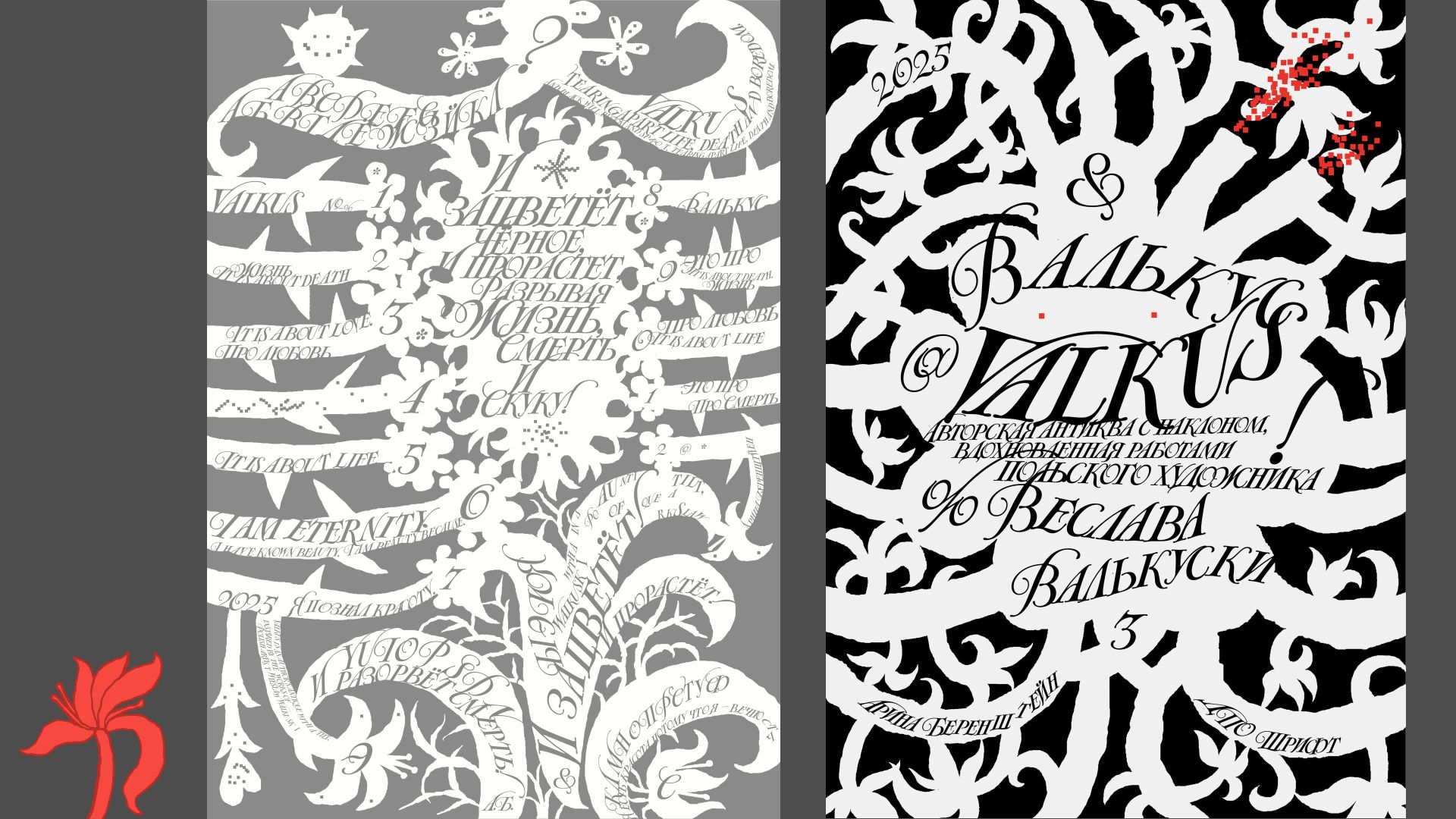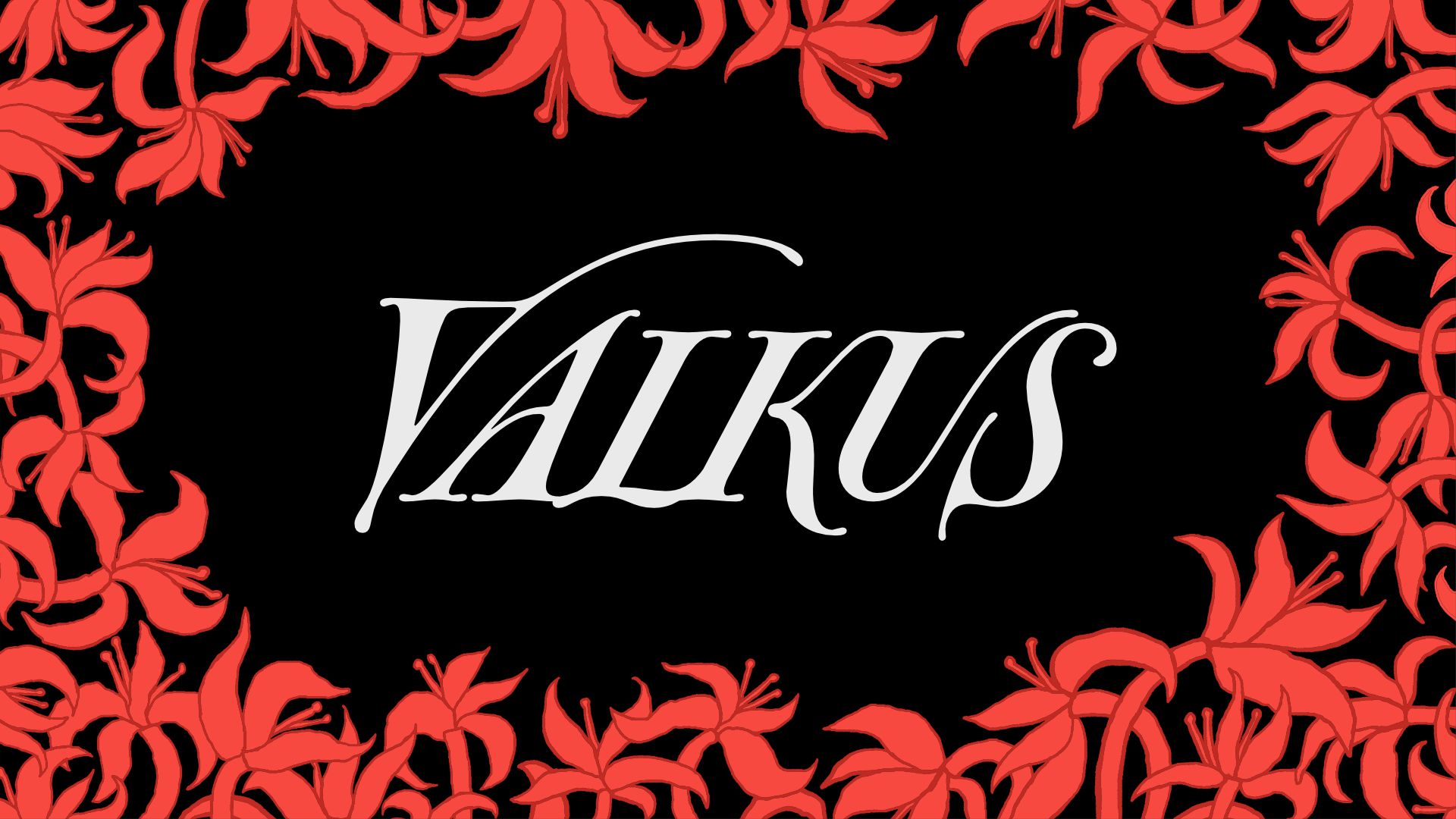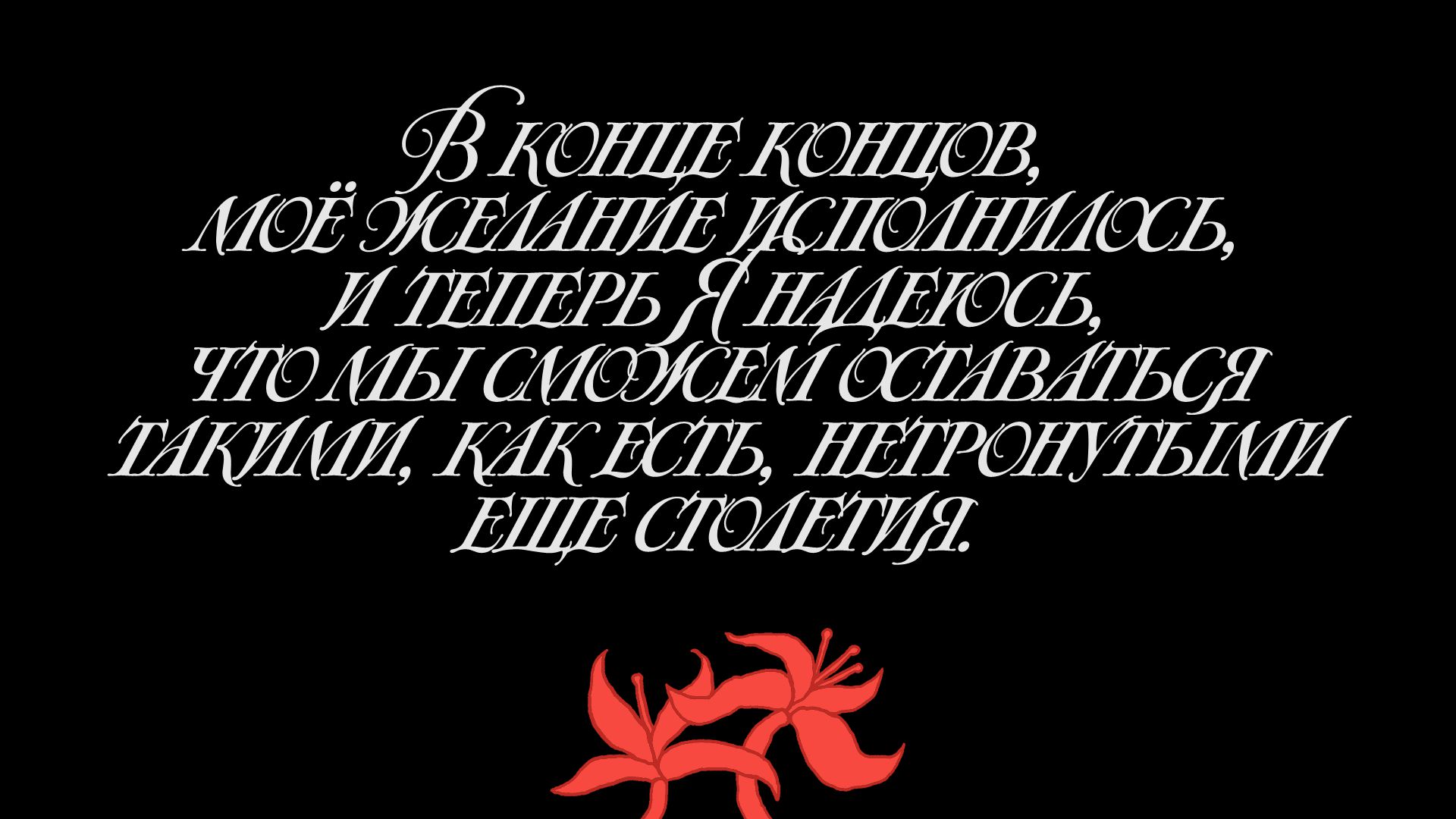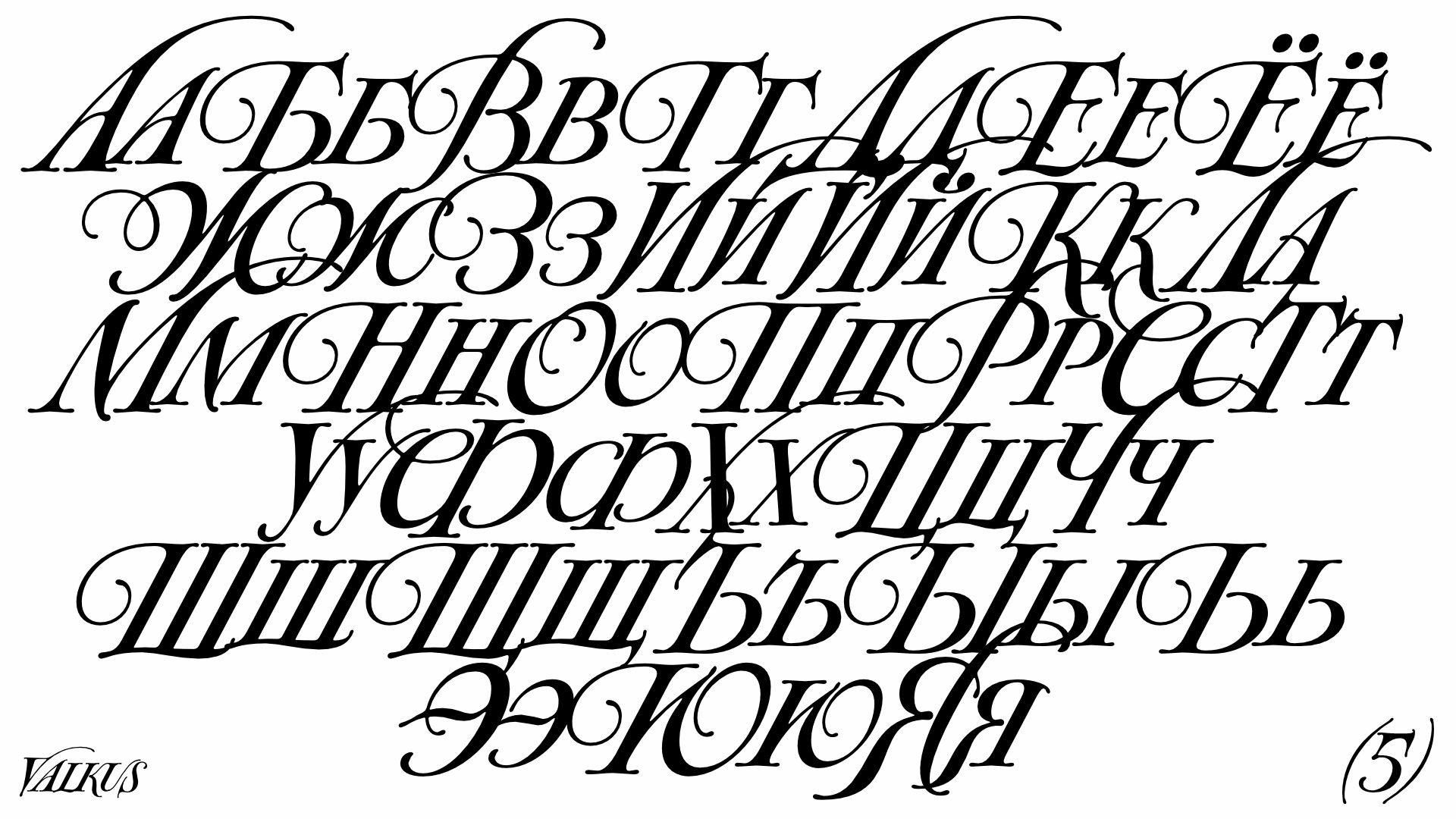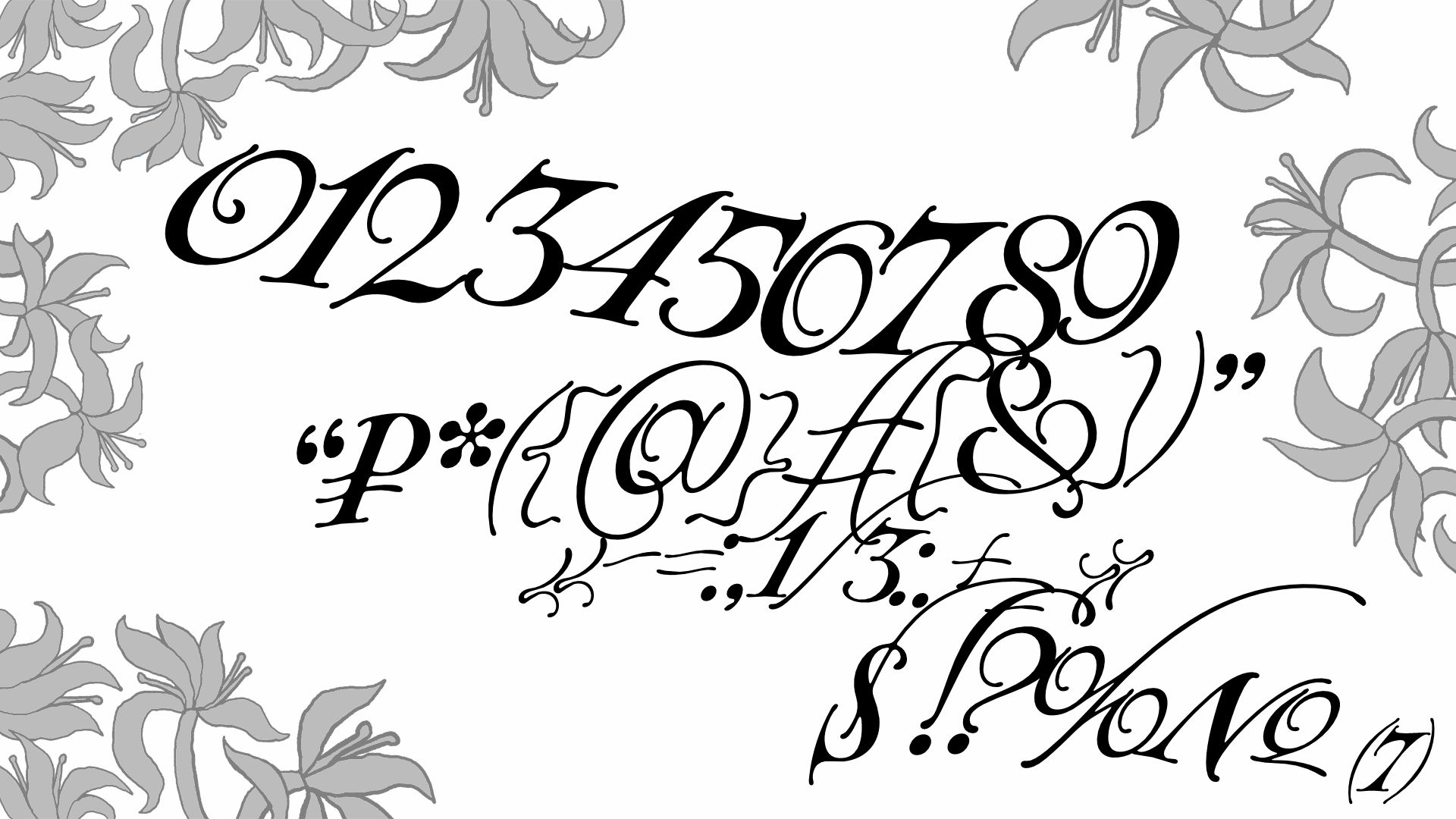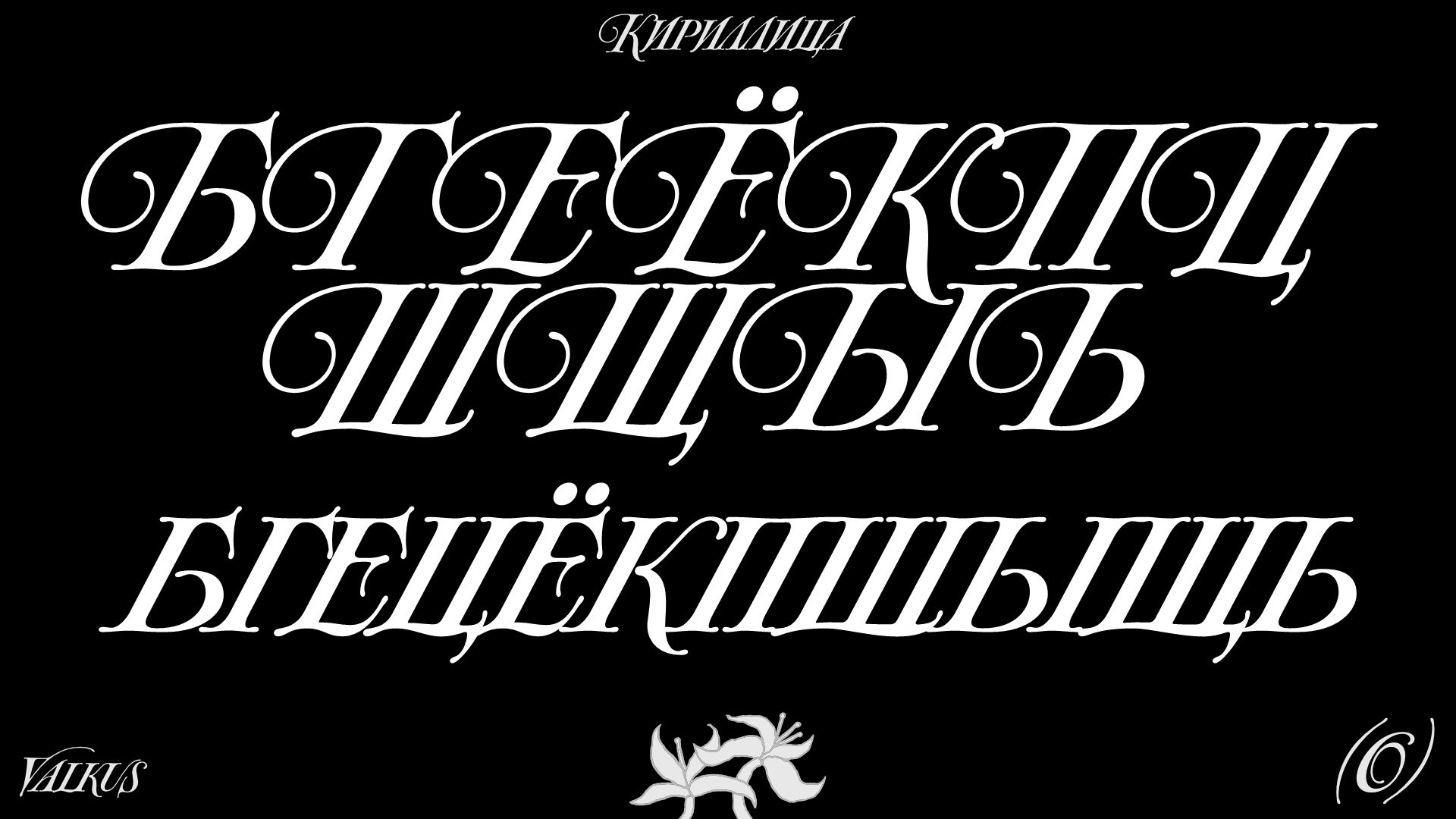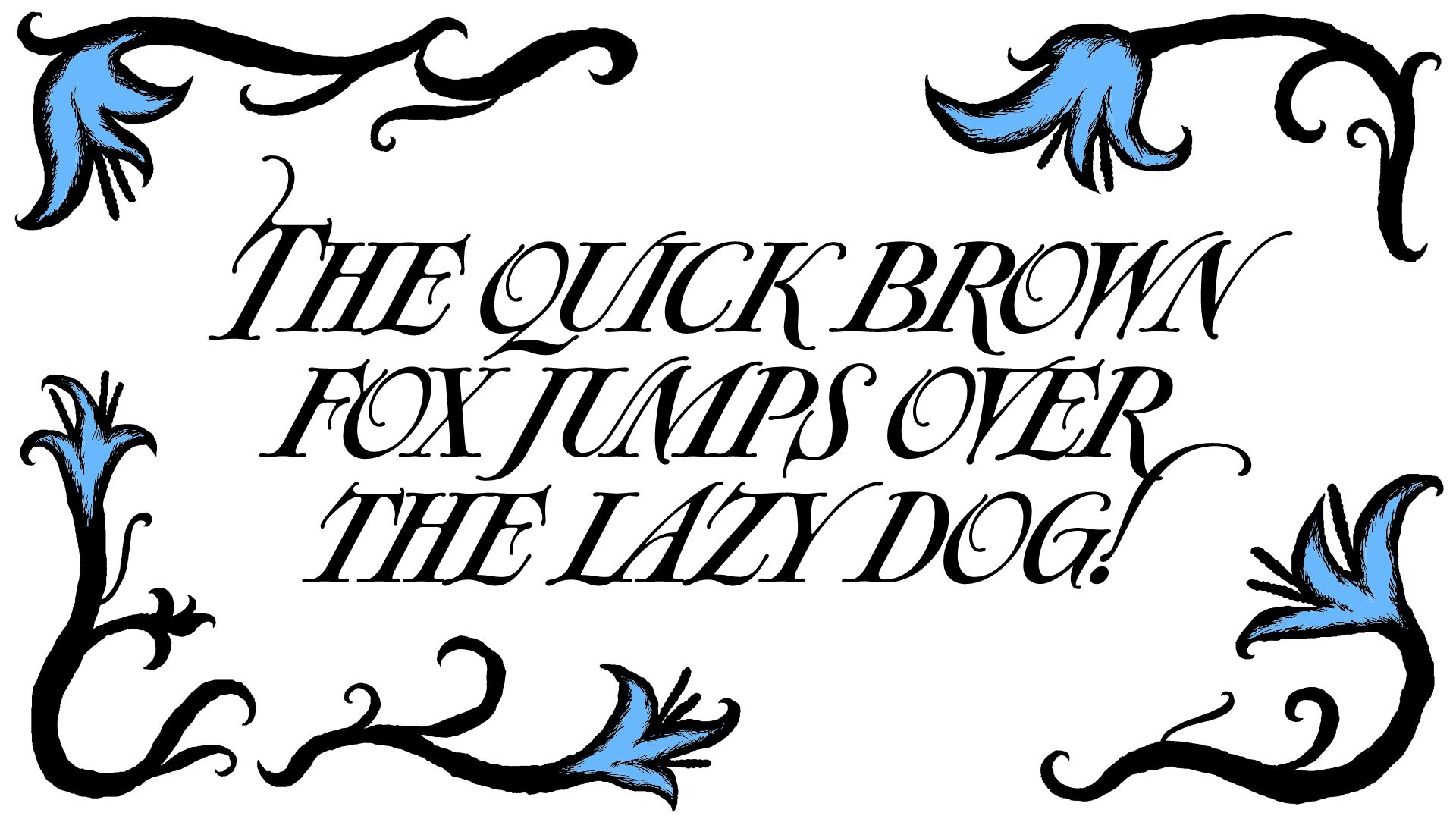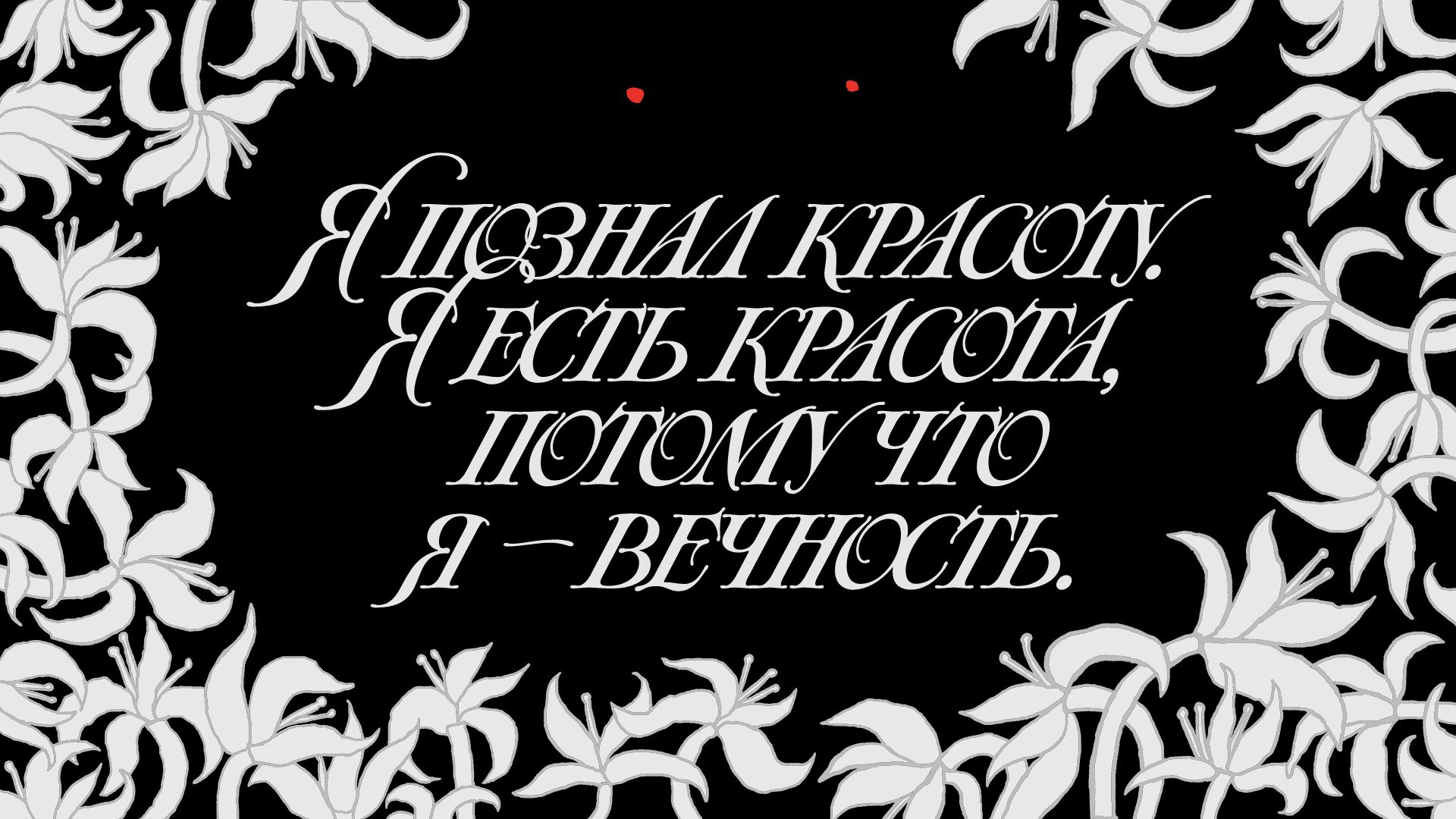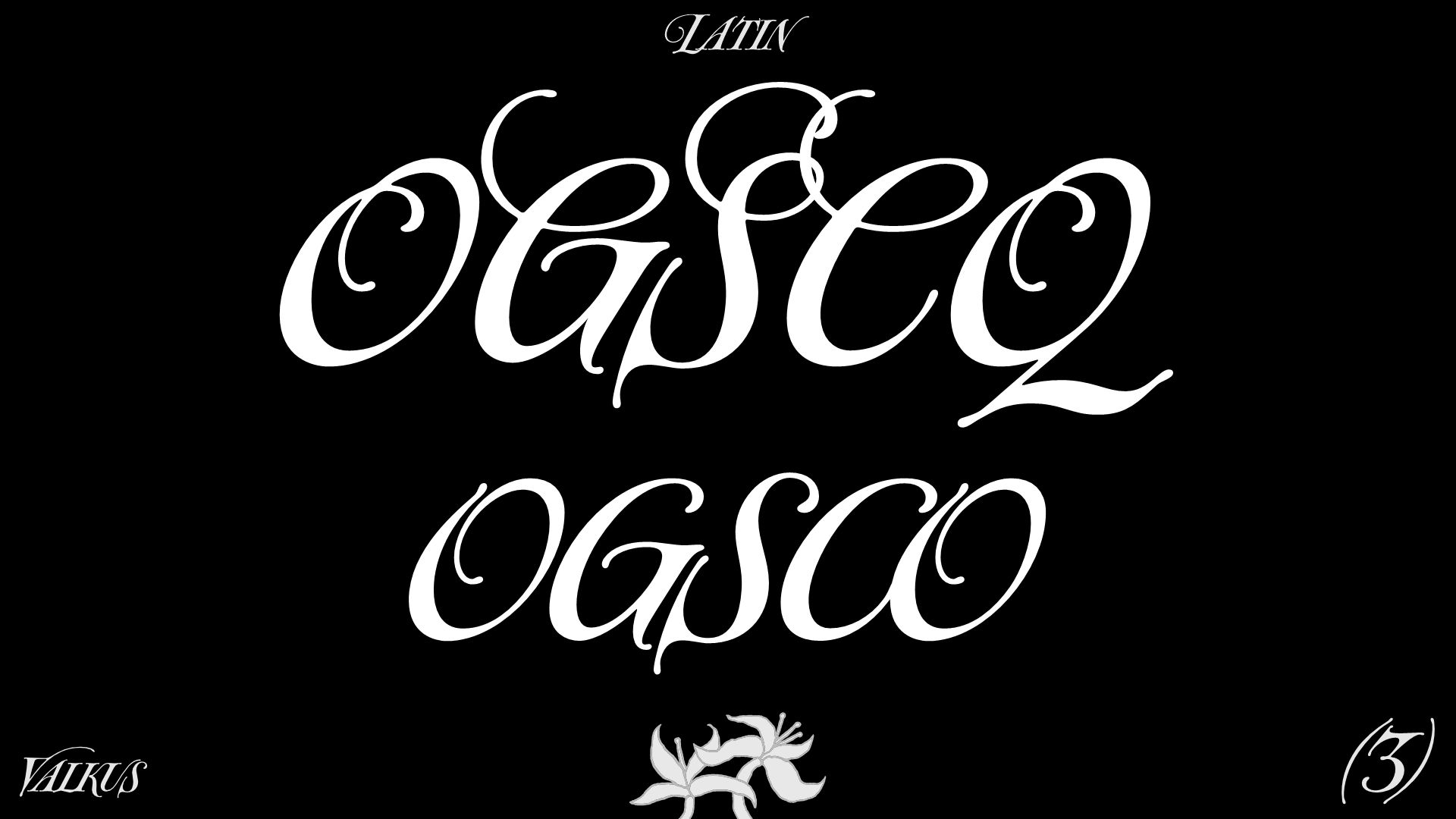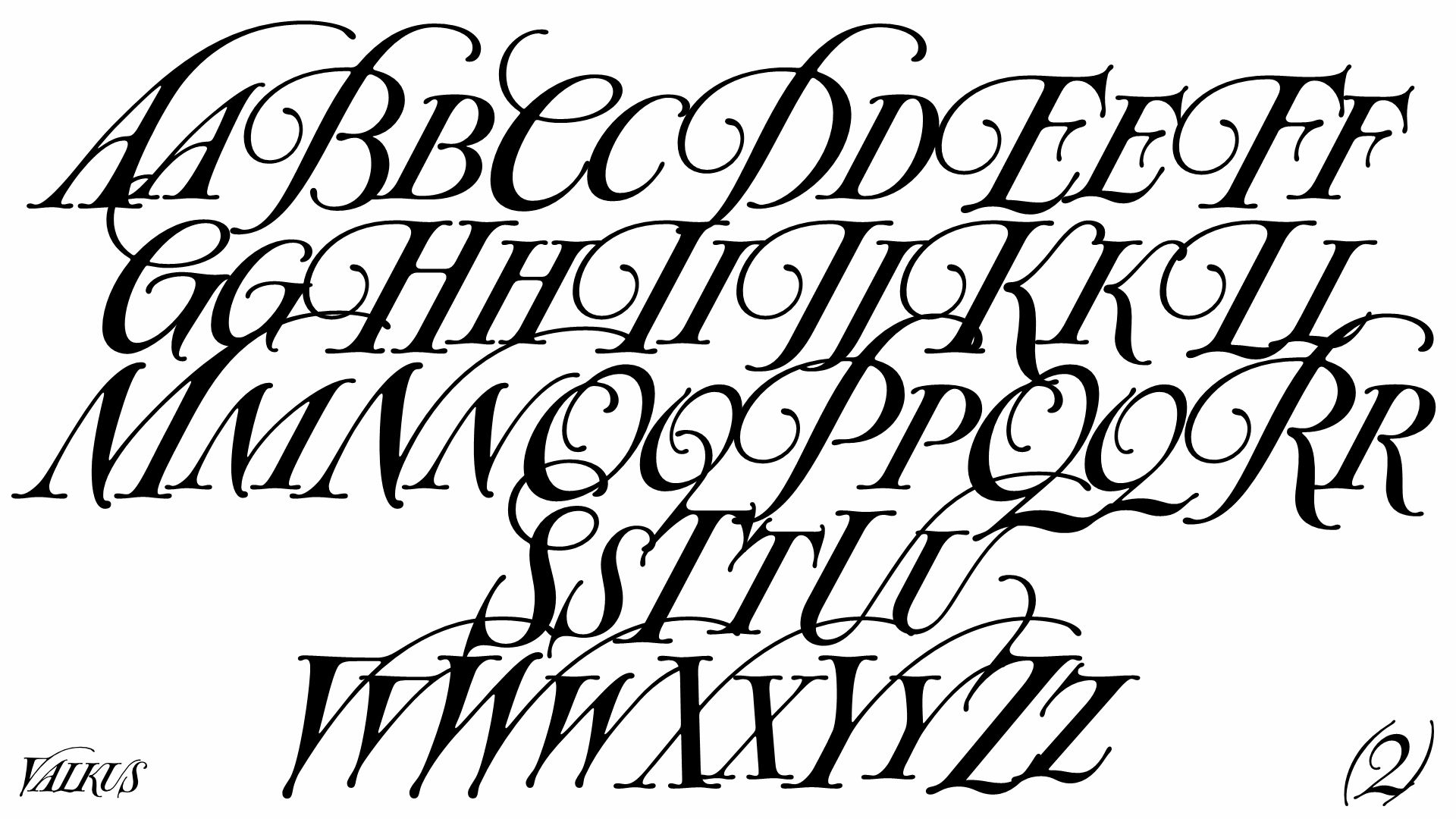
valkus
valkus — стильная современная авторская антиква с наклоном, вдохновлённая леттерингом на плакате веслава валькуски к оперному фестивалю.
у шрифта есть прописные/капители «для дома» и «парадные» прописные знаки. за счёт разных засечек буквы танцуют, кружат, топают, что позволяет набору быть живым, запутанным, особенным, плюс внутри букв ассиметричные скругления, которые подчёркивают его оригинальность. валькус впечатляет и мотивирует, он не стесняется, поэтому украсил себя набором всевозможных декоративных росчерков, завитков и капель.
когда я презентовала валькус, то придумала комикс про вампира, его последние слова звучали так: «я не нашел любовь, я познал красоту. я есть красота, потому что я вечность». хочется верить, что это про валькус.